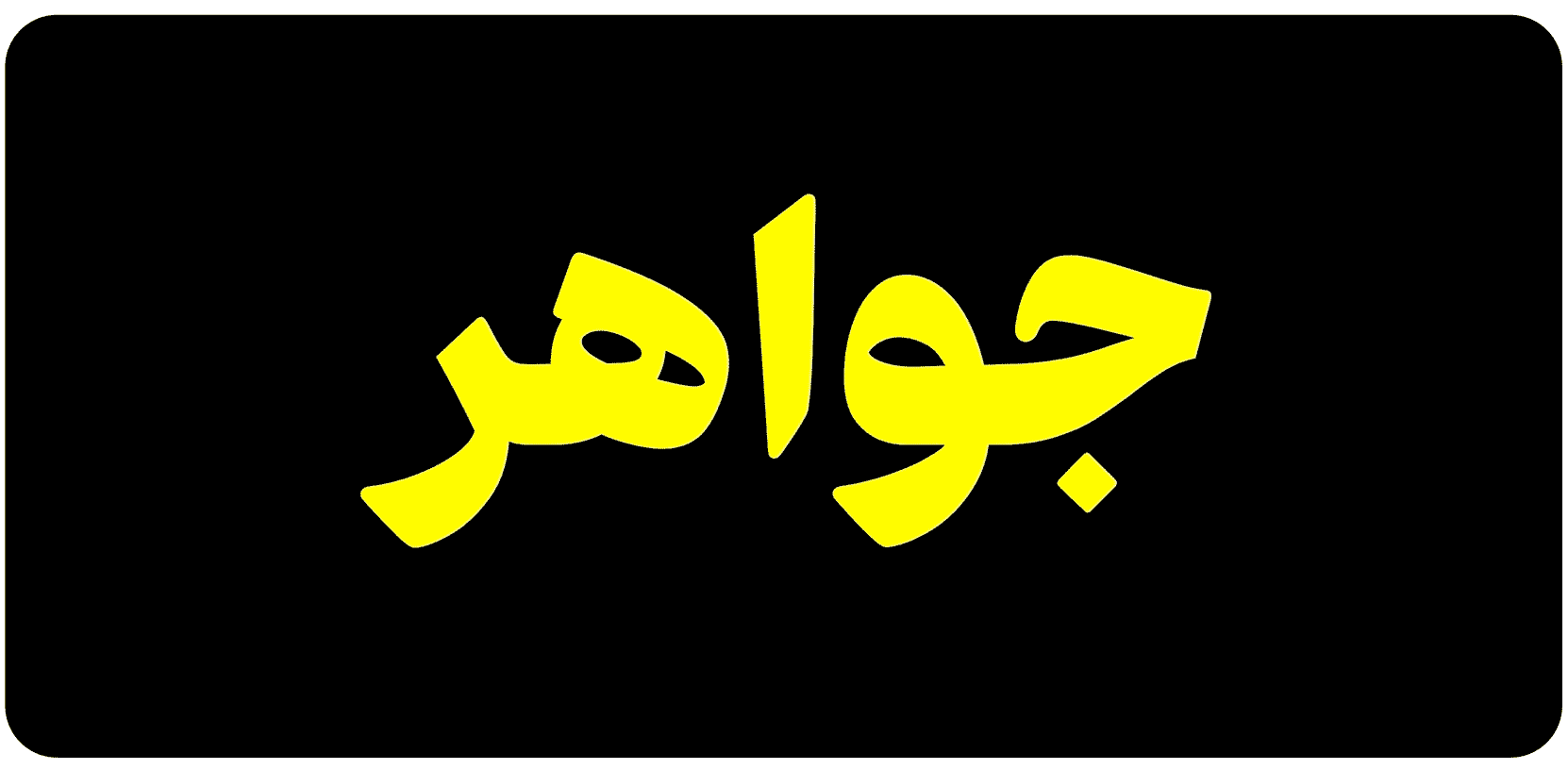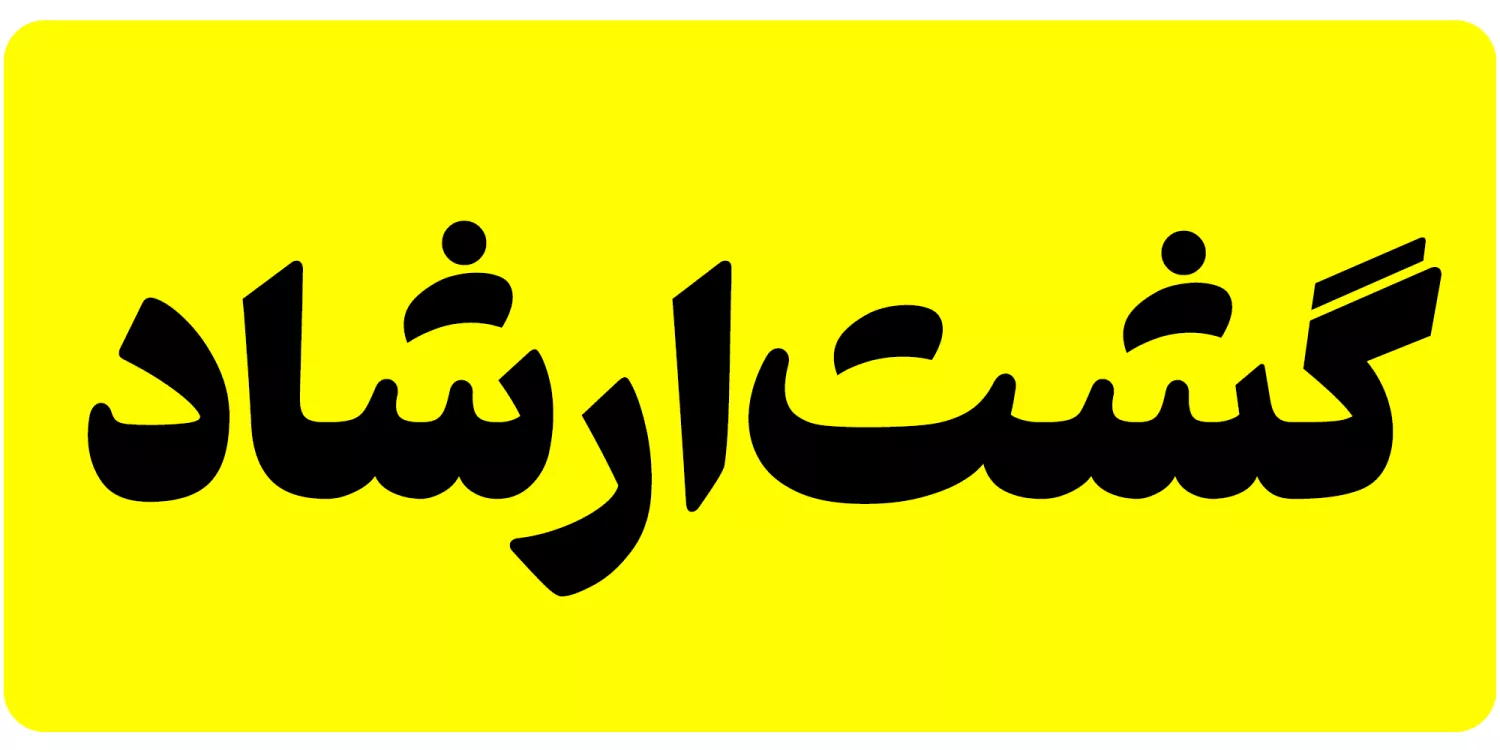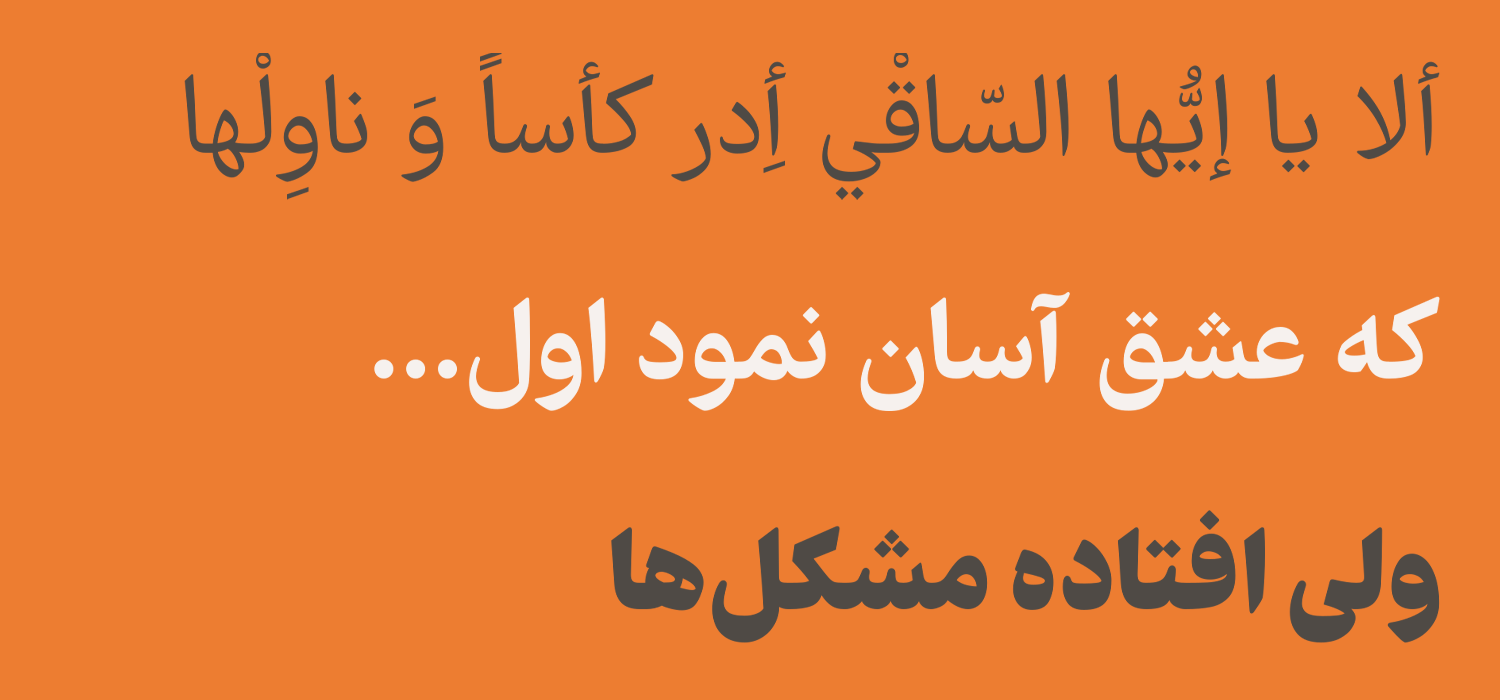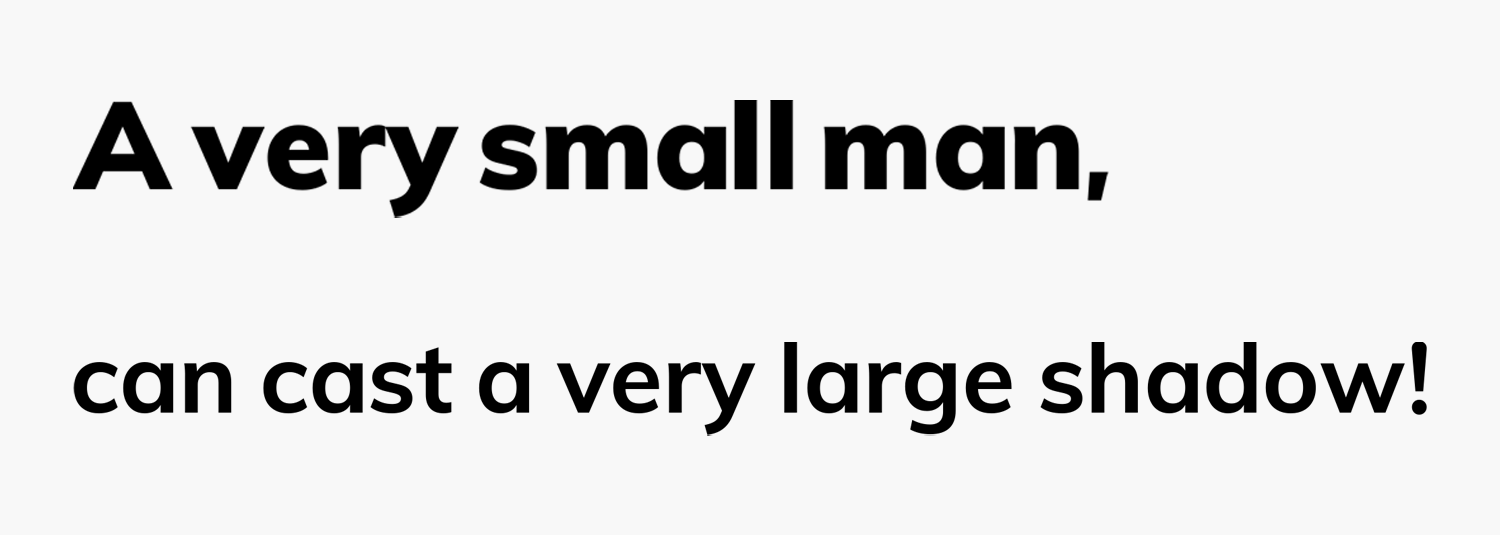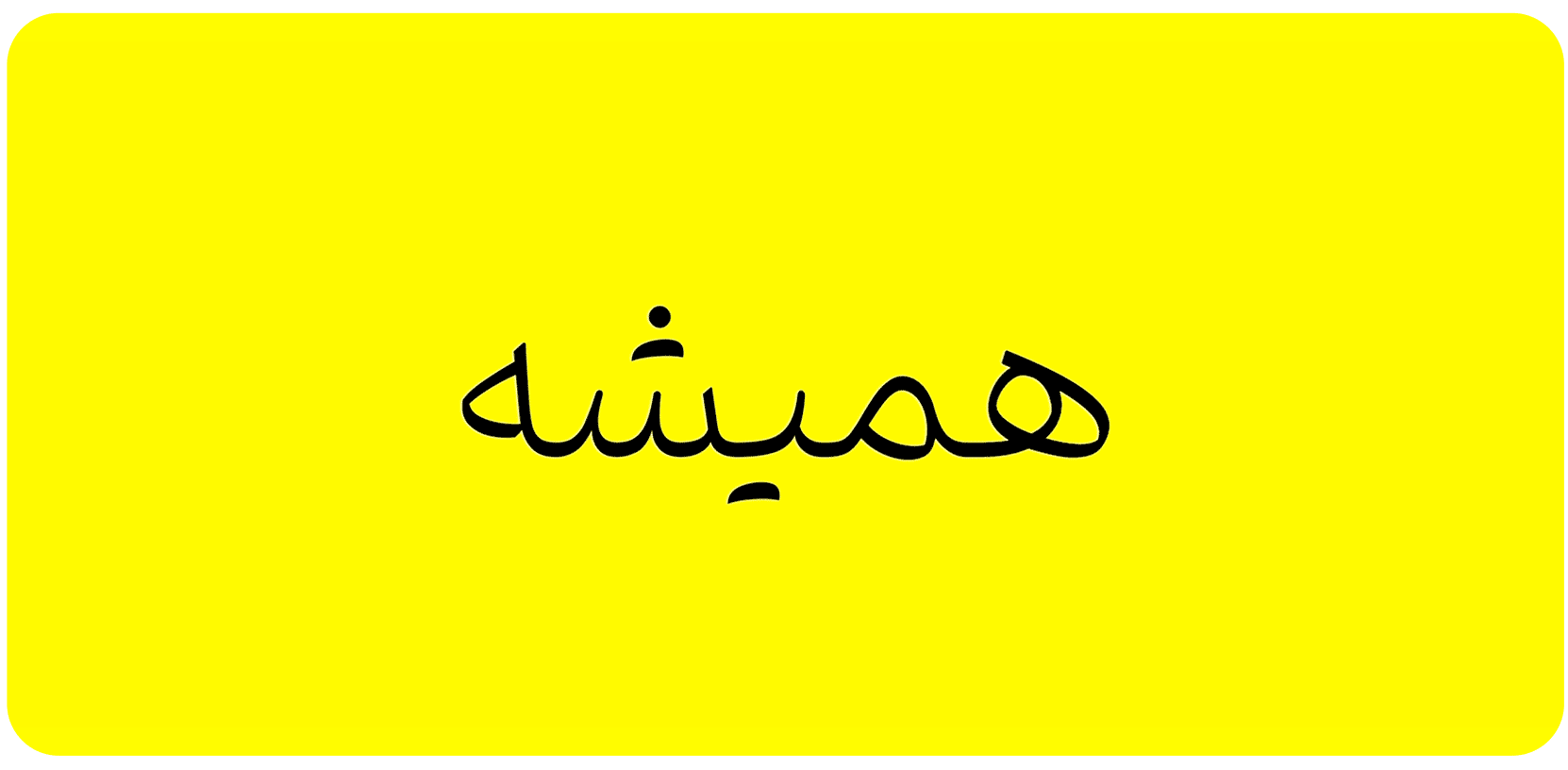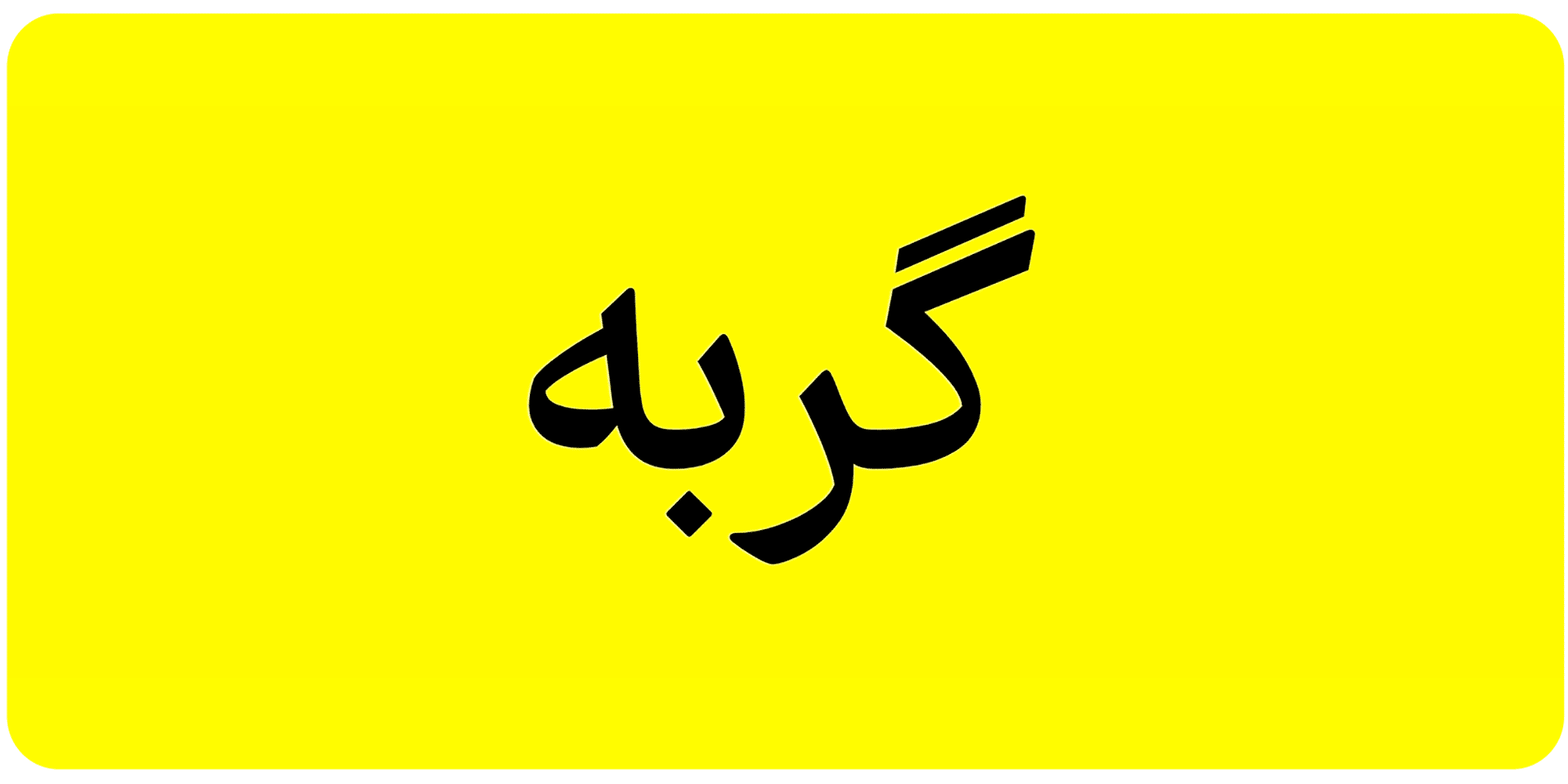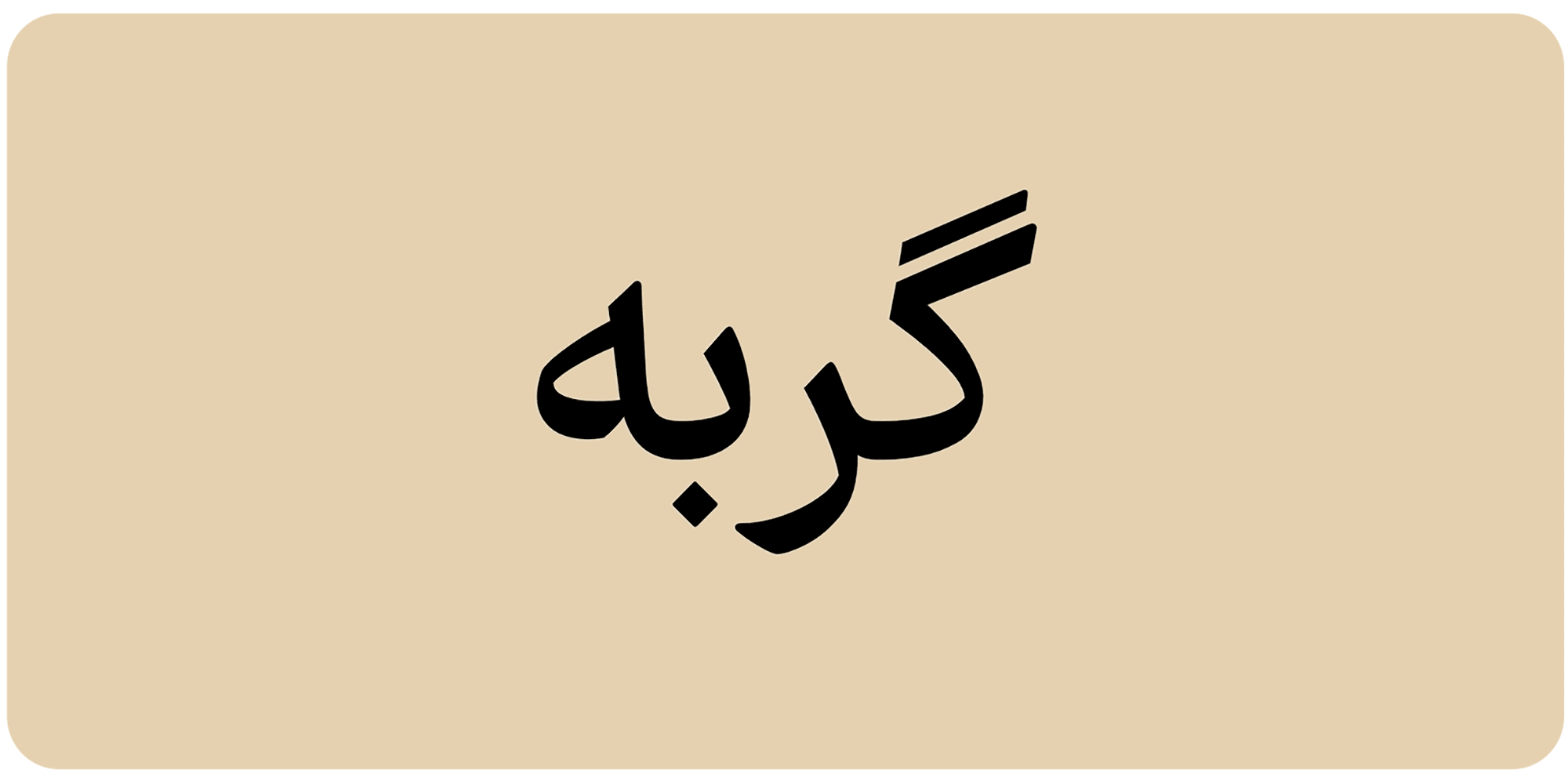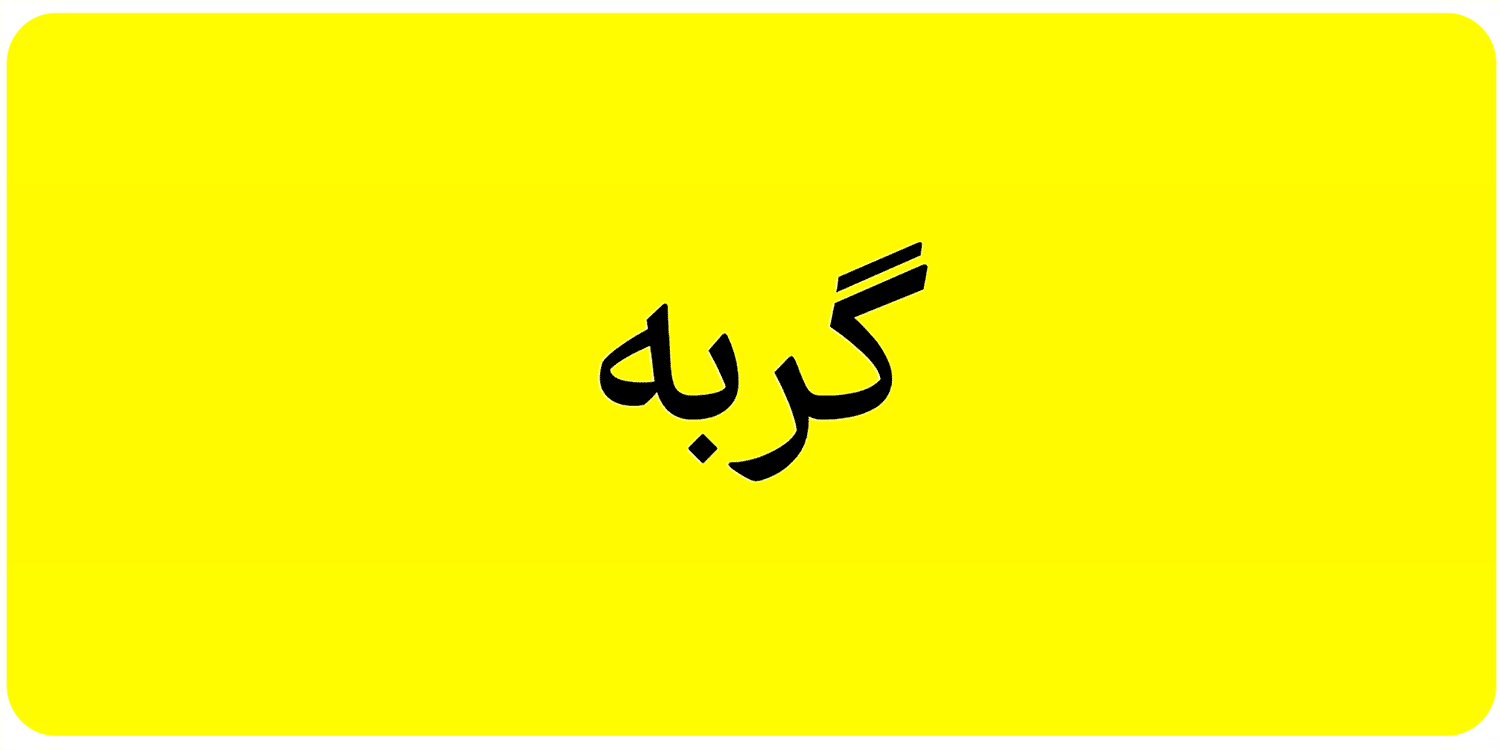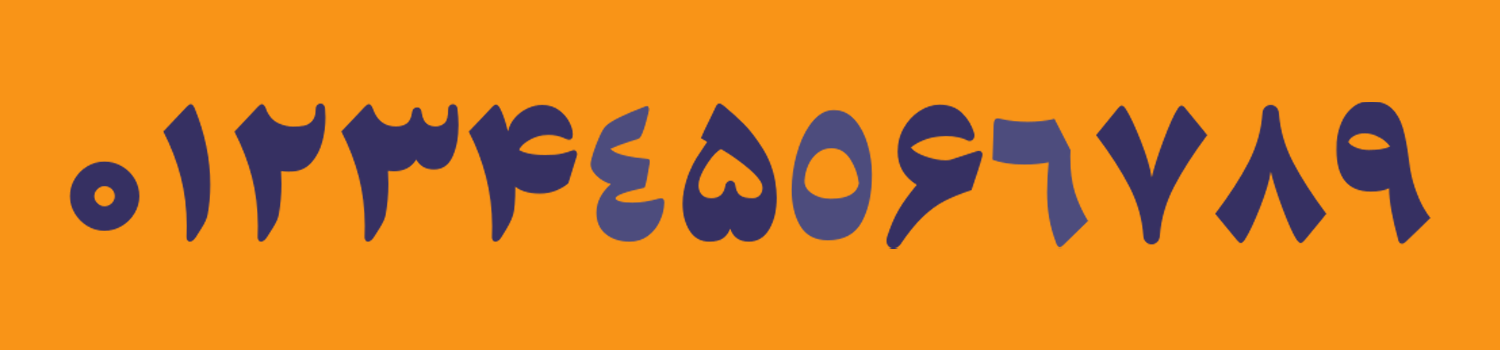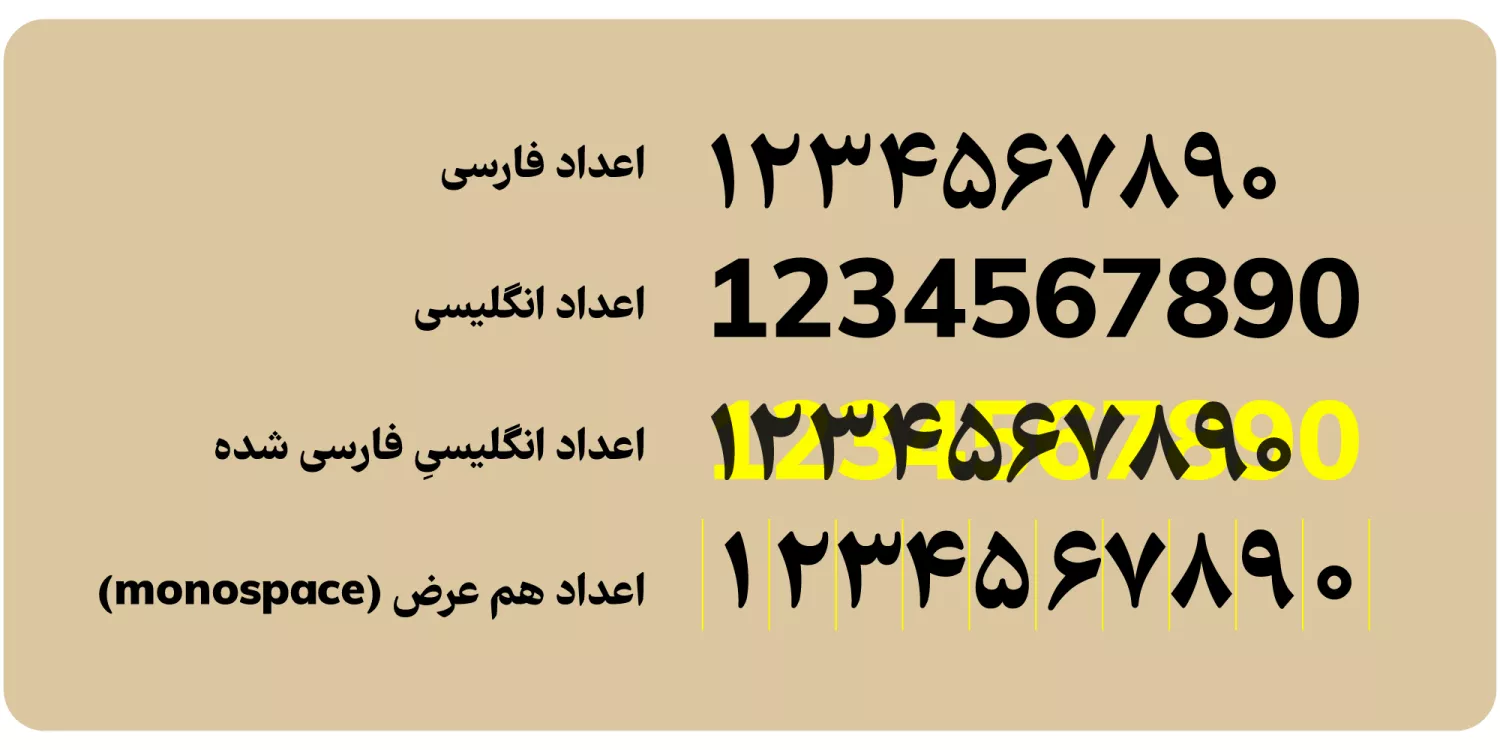
فونت فرهنگ (Farhang)
فونت فرهنگ (به انگلیسی: Farhang) در گروه فونتهای مناسب مطبوعات قرار دارد که بر اساس خط نسخ با الهام از فونتهایی مثل زر، نازنین و تیتر طراحی شده است. این قلم از ۹ وزن وریبل پشتیبانی میکند که میتوانید در هر دو فضای دیجیتال و چاپ استفاده کنید. فونت فرهنگ رایگان نیست و میتوانید آن را در سه بسته مختلف با وزنهای متنوع خریداری کنید.
فونت فرهنگ توسط مسلم ابراهیمی که پیش از این قلمهای دیگری همچون فونت ایران سنس و فونت دست نویس ایران سنس را معرفی کردیم طراحی شده است که تسعه این قلم را نیز شهرزاد اکبری به سرانجام رسانیده است. فونت دانا نیز به صورت مشترک توسط این دو طراح و توسعه دهنده ساخته شده است.
در ادامه این نوشته از سایت فونتچی به نقد و بررسی کامل فونت فرهنگ خواهیم پرداخت؛ قلمی که میتوانید از آن در متنهای کوتاه تا بلند با توجه به پشتیبانی که از وزنهای مختلف نازک تا سیاه دارد استفاده کنید که در کاربردهای مختلفی همچون مطبوعات و روزنامه، سایت و اپلیکیشن، طراحی رابط کاربری، صنایع چاپ و تبلیغات قابل استفاده است.
فونت فرهنگ براساس فونتهای نسخ رایج در مطبوعات ایران طراحی شده است که به همین دلیل استفاده از آن به عنوان بهترین فونت مطبوعات و چاپ بیشترین توجه را به خود اختصاص داده است.
استفاده از دور و منحنیهای زیاد، برشهای گرد و شکستگیهای محدود از مهمترین ویژگیهای تایپفیسهای حسین عبدالله زاده حقیقی (طراح فونتهایی نظیر زر، نازنین و تیتر) است. این ویژگیها در فونت فرهنگ حفظ شده است.
سبک طراحی و وزن فونت فرهنگ
فونتهای قدیمی فاقد تنوع وزن هستند. در همان ۲ یا ۳ وزن محدود هم معمولاً فرم حروف در وزنهای مختلف به هم مرتبط نیستند. اما در فونت فرهنگ طیف کاملی از ۹ وزن را با اسکلت و ساختار مشترک در اختیار دارید که با افزایش تدریجی وزن، تناسبات حروف تغییر نمیکند.
به دلیل وجود محدودیتهای حروفچینی در دستگاههای اولیه چاپ، جای نقطهها مایل به راست بود که این رسم در فونتهای دیجیتال نیز باقی مانده است.
در فونت Farhang نقطهها در جای درست خود یعنی زیر حرف مربوط به آن قرار دارند. حروفی مانند «ب، ب، ت، ت، پ، پ، ث، ث، ن، ن، ی، ی، س، س، ش، ش» گروه پر جمعیت خط فارسی هستند که شکل کاملا مشابهی دارند. چشم تنها با تشخیص نقطهها آنها را از هم تشخیص میدهد.
در فونت فرهنگ هر دندانه با توجه به حروف قبل و بعد خود جای نقطهٔ خود را طوری تعیین میکند تا نهایت نظم و زیبایی در شکل کلمات بدست آید.
در تمامی طیفهای ۹ وزن فونت فرهنگ امکان استفاده از ۲ شکل نقطه را در اختیار دارید که شامل نقطههای معمولی و نقطههای گرد و پیوسته هستند. چنین سبک نقطهگذاری در فونت هستی نیز وجود دارد.
همچنین نقطهها بصورت برنامهریزی شده در محل ایدهآل قرار میگیرند. بدون اینکه عرض حروف زیادتر شود یا فضای خالی بیش از حد پدید آید.
پشتیبانی از ۵ زبان متنوع
فونت فارسی فرهنگ علاوه بر این زبان از سایر زبانهای خاورمیانهای که بر اساس رسمخط فارسی هستند نیز پشتیبانی میکند که شامل زبانهای عربی، کردی و اردو میشود.
در تمامی این زبانها حروف مشترک یکسان در نظر گرفته شده است و در مواردی که حروف ساختاری متفاوت دارند با تنظیم صفحه کلید روی آن زبان تایپ خواهند شد.
به عنوان مثال در زبان عربی حروفی مثل «ک، ی، ه، ؤ، ئ» که ظاهری متفاوت از نظر نقطهگذاری یا همزه دارند پیادهسازی شده است. یا در زبان اردو حروفی مثل «ﮧ، ﮩ، ے» که متفاوت از فارسی هستند نیز پیاده سازی شده است.
البته حروف «ﮧ، ﮩ، ے» که مختص زبان اردو هستند، به عنوان حروف جایگزین در سایر زبانهای فارسی، عربی و کردی قابل استفاده است که در ادامه آنها را بررسی خواهیم کرد.
در تمامی زبانهای خاورمیانهای اعراب پشتیبانی شده و متناسب با زبان مورد نظر دارای همنشینی منظم و مشخصی با کاراکترهایی نظیر همزه و تشدید را دارند که به زیبایی متن نیز در وزنهای سنگین کمک میکند.
در فونت farhang انگلیسی از طراحی اختصاصی خبری نبوده و فونت اپنسورس Muli برای این قلم در نظر گرفته شده است که ساختاری هماهنگ داشته باشد. سعی شده تا سایز حروف همراه با افزایش و کاهش وزن تغییر نکند.
در تمامی وزنهای این قلم برای نسخه انگلیسی با مقدار بسیار محدودی افزایش ضخامت مواجه هستیم که با قرارگیری در کنار همان وزن با زبان فارسی کاملا مشهود است.
فونت فرهنگ وریبل با ۴ متغیر حرفه ای
در بسته دانلود رایگان فونت فرهنگ نسخه وریبل بر خلاف سایر فونتهای فارسی که محدود به یک تا سه متغیر هستند، از ۴ متغیر پشتیبانی میکند که امکان تغییر زوائد، کشیدگیها و شارپ کردن کلمات را علاوه بر وزن خواهد داد.
در نسخه وریبل به تمامی ۹ وزن این قلم همراه با امکانات خاصی که برای حروف جایگزین، اعداد فارسی و سایر قابلیتها دارد دسترسی خواهید داشت و لزومی ندارد که در محیط نرمافزار یا وب از تمامی وزنها به شکل جدا استفاده کنید. بلکه با نصب فقط یک فایل فونت به همه آنها دسترسی دارید.
در ادامه به معرفی هر یک از این ۴ متغیر میپردازیم که برای استفاده از آنها در محیط وب کافی است بر اساس فایل راهنما موجود در بسته دانلود فونت وریبل فرهنگ به کمک دستورات CSS و در محیط نرمافزاری به کمک تنظیمات OpenType این کار را انجام دهید.
اولین متغیر این قلم Weight است که امکان تغییر وزن فونت را مشابه تصویر فوق در اختیار قرار میدهد. میتوانید با تنظیم کردن این مقدار روی بازه ۱۰۰ که معرف وزن Thin تا بازه ۹۰۰ که معرف وزن Black است آن را مقداردهی کنید تا وزن فونت تغییر یابد.
متغیر دوم به نام Sharp شناخته میشود که از انحنا و گردی حروف در تمامی بخشهای بیرونی کاسته و ساختاری زاویهدار و چارگوش به آنها خواهد داد که این نوع فونتها را با نام فونت شارپ میشناسیم.